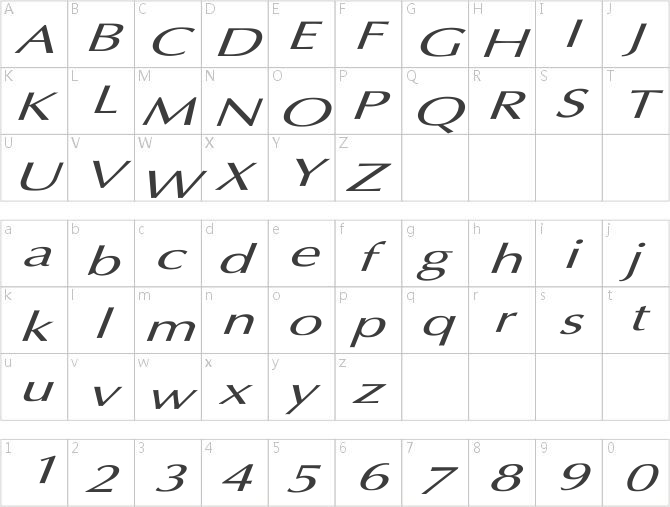
Optima-Italic-Ex-Italic
Optima-Italic-Ex-Italic介绍
Optima-Italic-Ex-Italic字体字库是一款让人赏心悦目、百看不厌的英文字体,适合各类广告和产品包装设计应用,字体大小0.16MB,格式为ttf字体,上传用户是哼哼哈兮,作者/版权方为未知
Optima-Italic-Ex-Italic效果图